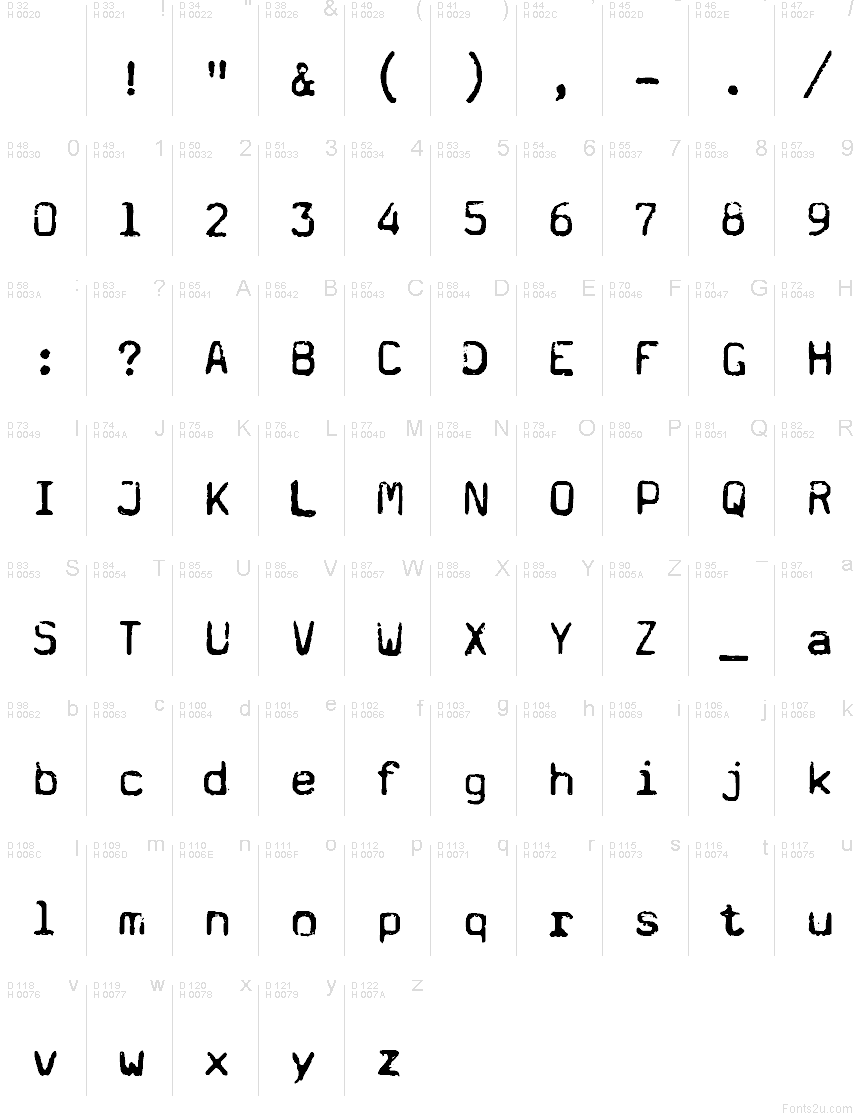
Dead postman - Respawned
Dead Postman Respawned od Mikea Larssona je bezplatné skreslené písmo typu display s ušpineným, napoly roztečeným vzhľadom, ktorý pôsobí ako vytiahnutý zo starých fotokópií a hororových fanzinov. Písmená sú ťažké, nepravidelné a majú drsné okraje, s vyhryznutými medzerami a mäkkými, opuchnutými krivkami, vďaka ktorým abeceda vyzerá skôr zbiedene ako len obnoseno.
Hodí sa na plagáty, obaly albumov, undergroundové letáky, titulky a streetwearovú grafiku, kde môže toto bezplatné písmo vniesť nádych drsnosti bez toho, aby skĺzlo k úhľadnému retro pastiche. Použite ho na krátke nadpisy, texty na obálkach alebo logotypy, keď chcete, aby typografia sama o sebe niesla náboj chaosu a napätia.